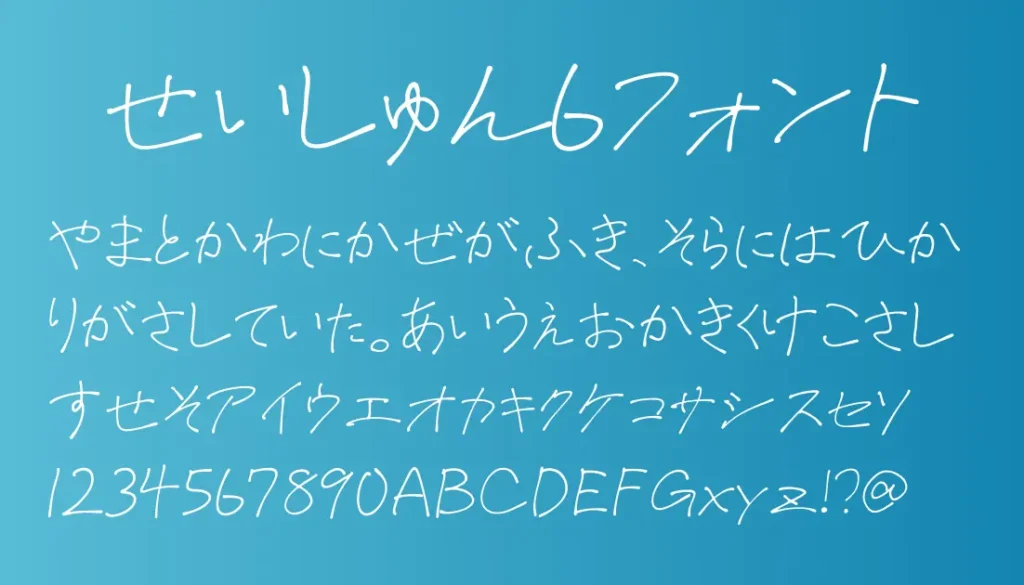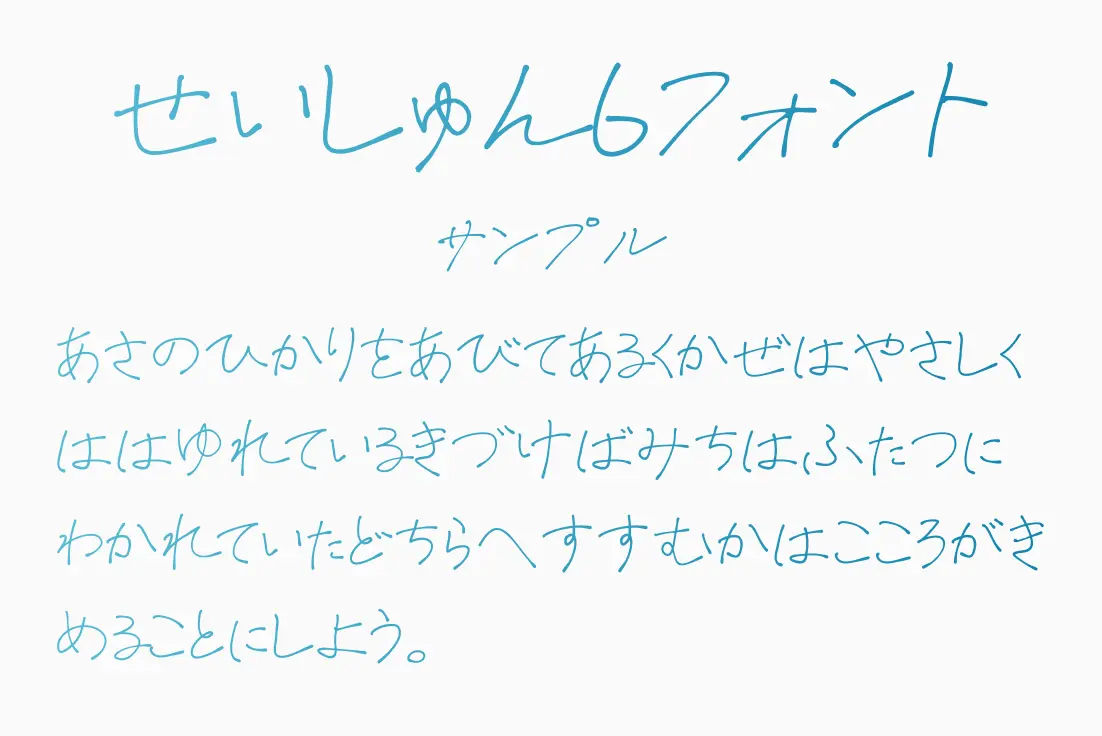
ボールペンでラフに書いたような細く軽やかな線が特徴の手書きフォント。少し跳ねるようなストロークやかすれが、学生時代のノートや手紙のような“リアルな青春感”を演出してくれます。整いすぎていない不均一さが逆にエモさを引き立て、MV字幕やSNS投稿、ラフなデザインにぴったり。使いどころは選ぶけど、ハマると一気に世界観を持っていくクセ強フォントです。
青春6フォント